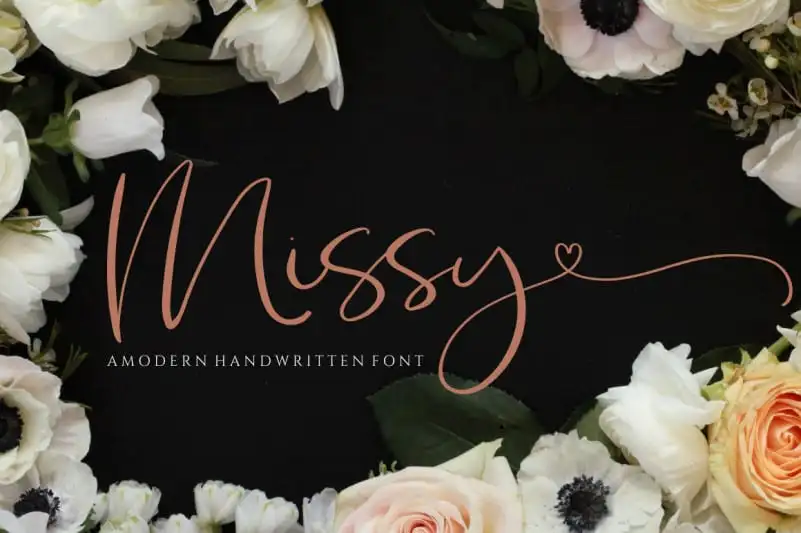
Introduzimos a Missy Script Font, uma elegante e feminina tipografia moderna que destaca-se por sua feminilidade e elegância. Ideal tanto para logotipos quanto para materiais de marcação ou para embalagens de eventos, esta fonte é perfeita para cartões de aniversário, campanhas sociais, sobretudos e muito mais. Com a Missy Script Font, sua identidade visual ganha um ar sofisticado e pessoal, especialmente quando combinada com as linhas suaves e femininas desta fonte. Acompanhe o design da ReyreyBlue, uma designer talentosa que criou este recurso gráfico, disponível para quem deseja adicionar personalidade a seu próximo projeto visual. Engane-se se acha que a Missy Script Font é apenas outra tipografia. Ela é um truque de magia que irá transformar seus materiais digitais em verdadeiros trabalhos de arte.